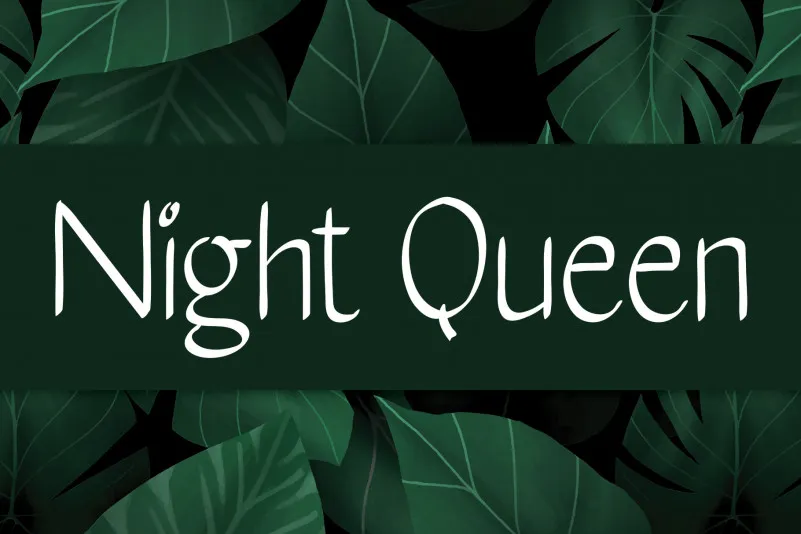
A Night Queen Handwritten Font é uma fonte de escrita a mão simples e redonda que captura a essência do desenho natural da mão humana. Suas letras têm um ar acolhedor, perfeitamente adaptado para um uso criativo em designs variados. Essa fonte não apenas oferece beleza pura, mas também flexibilidade suficiente para criar trabalhos de design impressionantes e únicos. É uma escolha ideal para quem busca personalidade e elegância no seu próximo projeto gráfico. Seja você um designer que quer trazer vida a cada palavra ou um profissional que precisa de um toque especial em sua próxima peça, a Night Queen Handwritten Font está aqui para dar o ponto final perfeito ao seu trabalho.